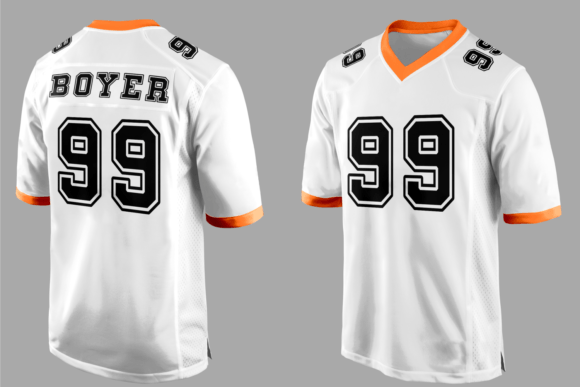
Second Pointed Font – خط عصري أنيق لمشاريعك الإبداعية
ارتقِ بتصاميمك مع Second Pointed Font، الخط المميز الذي يجمع بين الحداثة والوضوح. يتميز هذا الخط بحوافه الحادة ولمساته العصرية، مما يجعله مثاليًا للاستخدام في التصاميم الفاخرة، الشعارات، العناوين الجذابة، والمطبوعات الإبداعية.
???? المميزات:
✔️ تصميم أنيق وعصري يناسب مختلف الاستخدامات
✔️ وضوح عالي وسهولة في القراءة
✔️ مثالي للعلامات التجارية، التصاميم الرقمية، والمطبوعات
أضف لمسة احترافية إلى أعمالك الإبداعية مع Second Pointed Font، واجعل تصاميمك أكثر تميزًا وتأثيرًا! ????✨